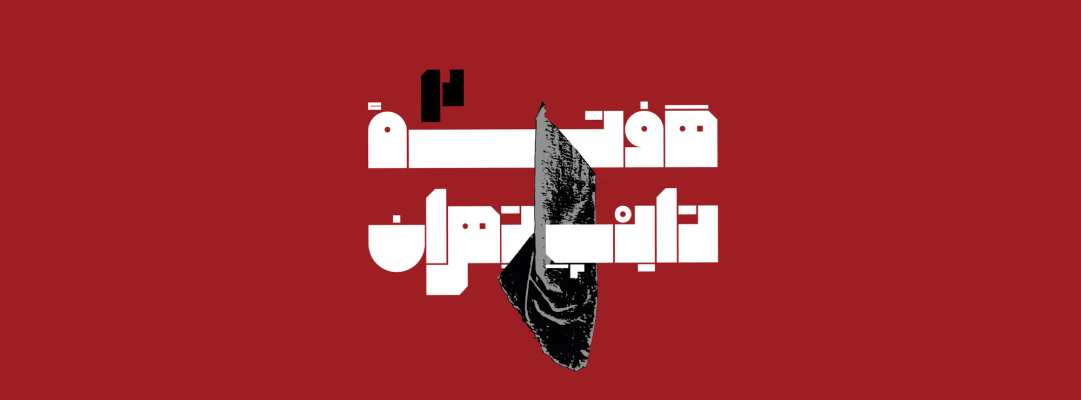
دومین رویداد هفته تایپ تهران با حضور استاد احصایی
مراسم افتتاحیه دومین رویداد «هفته تایپ تهران» در دو بخش نشستها و نمایشگاه برگزیدگان تایپ فارسی روز جمعه دوم آذرماه ۱۴۰3 با حضور پیشکسوتان این حوزه در خانه هنرمندان ایران برگزار شد.
در این مراسم افرادی چون اسدالله چهرهپرداز؛ کامران انصاری؛ بهرام کلهرنیا، رئیس هیئتمدیرهی انجمن صنفی طراحان گرافیک؛ سعید باباوند، نایب رئیس انجمن صنفی طراحان گرافیک ایران؛ علیرضا وکیلی ورجوی، امراله فرهادی، هومن عباسپور و مهناز مقدسی، نایب رئیس و دبیر انجمن صنفی ویراستاران؛ ناصر آذرشب، مدیر مسئول نرمافزاری مریم؛ مسلم ابراهیمی، مدیر مسئول فونت ایران؛ عاطفه محمدی، دبیر رویداد؛ اعضای شورای مشاوران و برنامهریزی اجرایی رویداد حضور داشتند.
جلسات سخنرانی این رویداد، علاوه بر حضوری، به صورت آنلاین ارائه شد. شرکتکنندگان این رویداد از شهرهای تهران، اصفهان، شیراز، مشهد، همدان، رشت، نیشابور، تبریز، قزوین، یزد، لرستان، قم، نوشهر، اهواز، هرمزگان، سیستان و بلوچستان، کردستان و کاشان بودند.
رویداد با حضور انجمن صنفی طراحان گرافیک ایران، انجمن صنفی ویراستاران، مدرسه ویژه و کوییکاستودیو آغاز شد.
عاطفه محمدی، دبیر رویداد گفت: دومین رویداد هفته تایپ تهران با قصد فراهمآوردن فضایی برای نشر تجارب طراحان و توسعهدهندگان و نیز نتایج پژوهشهای پژوهشگران و برقراری ارتباط بین فعالان حوزۀ تایپ فارسی، ناشران، نویسندگان، ویراستاران، طراحان گرافیک، طراحان محصولات دیجیتال، توسعهدهندگان و پژوهشگران رشتههای مرتبط با آن، چون علوم شناختی و عصبشناسی، توانبخشی و بهزیستی، طراحی، زبانشناسی و جامعهشناسی برگزار میشود.
کمبود منابع آموزشی بهخصوص در زمینهی قلمهای غیرلاتین، مانند فارسی، همواره مانع بزرگی برای طراحان در مسیر رشد در این حوزه ساخته است و به نظر میرسد یکی از راههای تولید منابع آموزشی و پژوهشی همافزایی دانش فعالان این حوزه و کاربران آن باشد؛ چرا که هر یک از ما منبعی غنی از تجارب و فعالیتهای علمی و پژوهشی هستیم که لازم است آنها را مدون و ثبت و منتشر کنیم.
نمایشگاهی از آثار یک سال اخیر طراحان تایپ فارسی دایر کردهایم تا آثار طراحان تایپ فارسی در یک سال اخیر نیز همچون سال گذشته ثبت شود تا فرصتی باشد برای ثبت مسیر تاریخی تایپ فارسی و به نمایش درآمدن تحولات آن و مهمتر از آن، ارتباط بیشتر طراحان با یکدیگر و شناساندن آثارشان به مخاطبان و کاربران.
وی هم چنین افزود: رویکرد سخنرانیها را انتقال تجربه در نظر گرفتیم تا بیشتر با نتایج فعالیتهای طراحان و نیازهای کاربران فونت آشنا شویم. با توجه به این هدف برای ارتباط بیشتر شرکتکنندگان در این رویداد با یکدیگر و ساخت ارتباطات جدید، یک بازی با همکاری مجموعه فونت ایران ترتیب داده شد تا با تکمیل روند این بازی، فرصتی برای گفتگو افراد با یکدیگر فراهم شود.
در این مراسم پنج سخنرانی و دو میزگرد همراه با پرسش و پاسخ برگزار شد. ازجمله موضوعات مطرحشده در این گفتوگوها میتوان به پیادهسازی اپتیکال سایز، کلید تشخیص یا خوانایی حروف، طراحی تایپهای بیانگر برای بهبود خواندن در افراد نوخوان، مسیر طراحی تایپهای سفارشی و بررسی روند تحولات فونت فارسی در چند سال اخیر اشاره کرد.
نشستهای تخصصی
در روز سوم آذر ماه دو نشست تخصصی با موضوعات معیارهای سنجش و داوری فونتهای فارسی و فونتهای آزاد و مسائل حقوقی آنها، با همراهی داوران بخش تجربی نمایشگاه رویداد، مدیران فروشگاههای فونت (نرمافزاری مریم و فونت ایران)، نمایندگان انجمن صنفی ویراستاران و عضو هیئت مدیره آزادیهای دیجیتال در مدرسه ویژه برگزار شد.
در چهارم آذرماه، استاد برجسته هنرهای تجسمی ایران، سید محمد احصایی، به همراه اعضای هیئت مدیره انجمن صنفی گرافیک ایران از نمایشگاه هفته تایپ تهران بازدید به عمل آوردند.
ایشان در این بازدید ضمن ابراز خوشحالی و حمایت از برگزاری این رویداد مهم، بر اهمیت استمرار و تداوم آن در راستای ارتقای جایگاه تایپ فارسی تأکید کردند. این حضور ارزشمند، نشان از توجه ویژه جامعه هنری و گرافیکی کشور به نقش تایپ فارسی در هویت بصری معاصر دارد. حضور چنین چهرههای تأثیرگذاری، اعتبار و انگیزهای مضاعف برای برگزارکنندگان و جامعه طراحان تایپ فارسی فراهم میآورد.